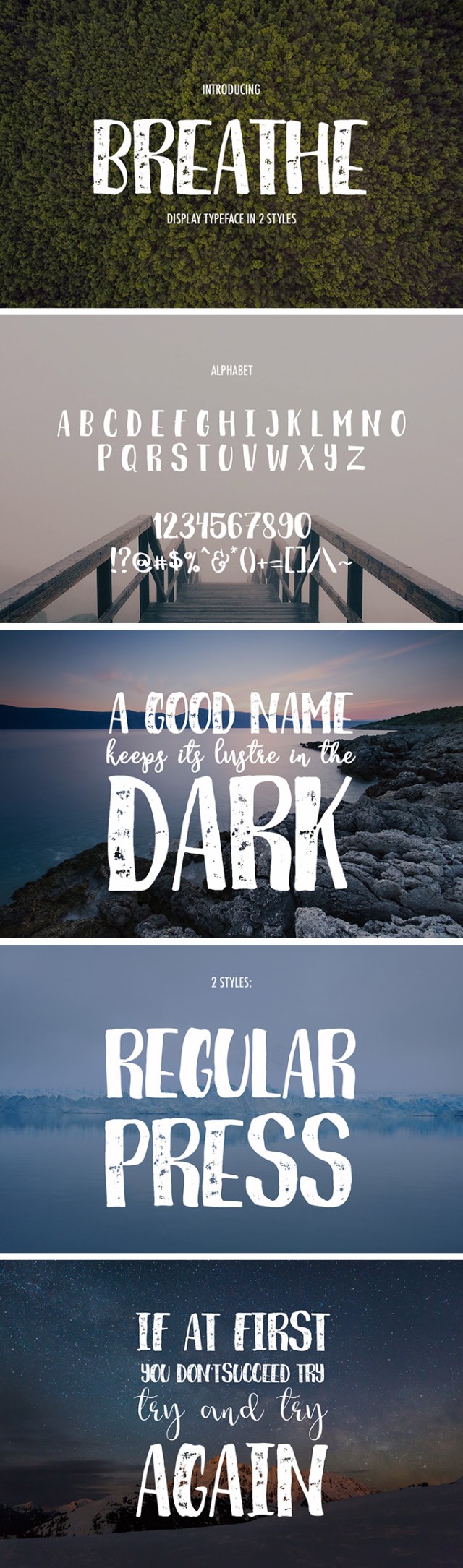
Breathe, tipografía decorativa GRATIS
Para acabar con esta semana y coger el puente con fuerza (esto va sólo para los de Madrid) os dejo una tipografía decorativa muy efectiva para cabeceras. La licencia es libre así que podéis utilizarla tanto para proyectos personales como comerciales. Para descargarlo pulsad sobre la imagen o en el link del pie de la entrada. Espero que os sirva y recordad que los like y los follow ayudan mucho así que visitadnos en Twitter y Facebook. También nos podéis encontrar en Flipboard buscando nuestra revista El Arquitecto de Ilusiones.